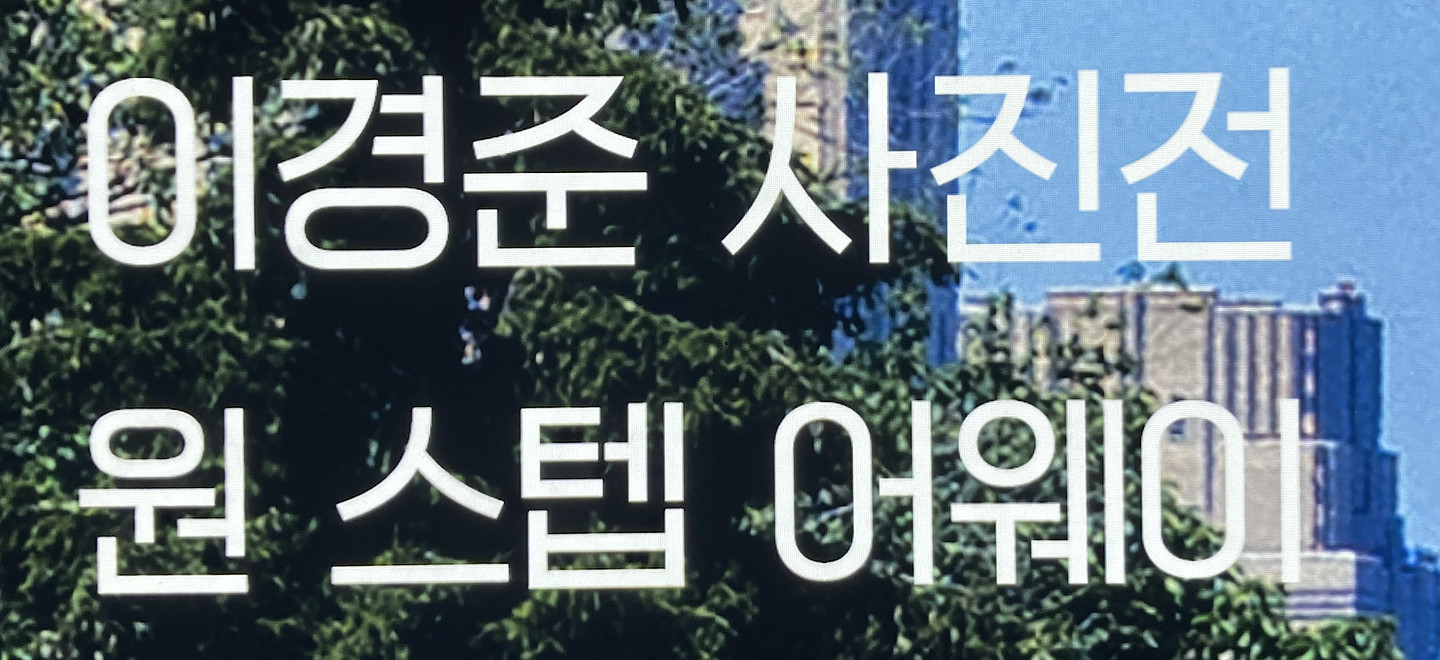
그라운드 시소 센트럴점에서 진행하는 사진전에서 본 서체입니다. 아무리 검색해도 나오질않아 혹시 아시는 분 있을까요?
각진펜
준폰트의 각진펜입니다. 굵기는 40~50으로 보이네요. https://joonfont.com/shop/angledpen https://www.sandollcloud.com/font/17366.html